Gràffica Nº41 llega con una de sus ediciones más completas dedicadas a la tipografía, reuniendo a algunas de las fundiciones más influyentes del panorama internacional y acompañada de contenidos exclusivos que amplían la experiencia de lectura.
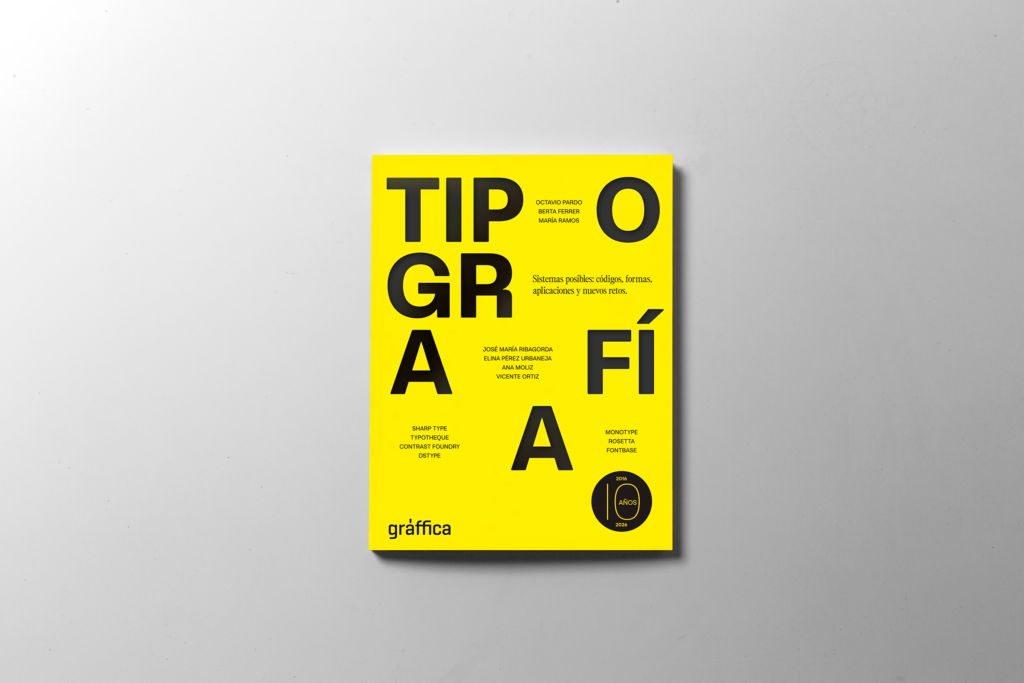
El número incluye entrevistas en profundidad con estudios y actores clave como Sharp Type, Typotheque, Contrast Foundry, DSType, Monotype y Rosetta. Un recorrido que permite entender cómo se está construyendo hoy la tipografía a escala global: desde grandes sistemas tipográficos para plataformas como YouTube hasta desarrollos multiscript de enorme complejidad como Zed, una tipografía pensada para cientos de idiomas y contextos.
Además, esta edición incorpora el espécimen de Zed, un cuaderno de 80 páginas desarrollado por Typotheque que permite explorar en detalle uno de los proyectos tipográficos más ambiciosos de los últimos años. Una pieza que convierte la revista en un objeto editorial aún más completo.
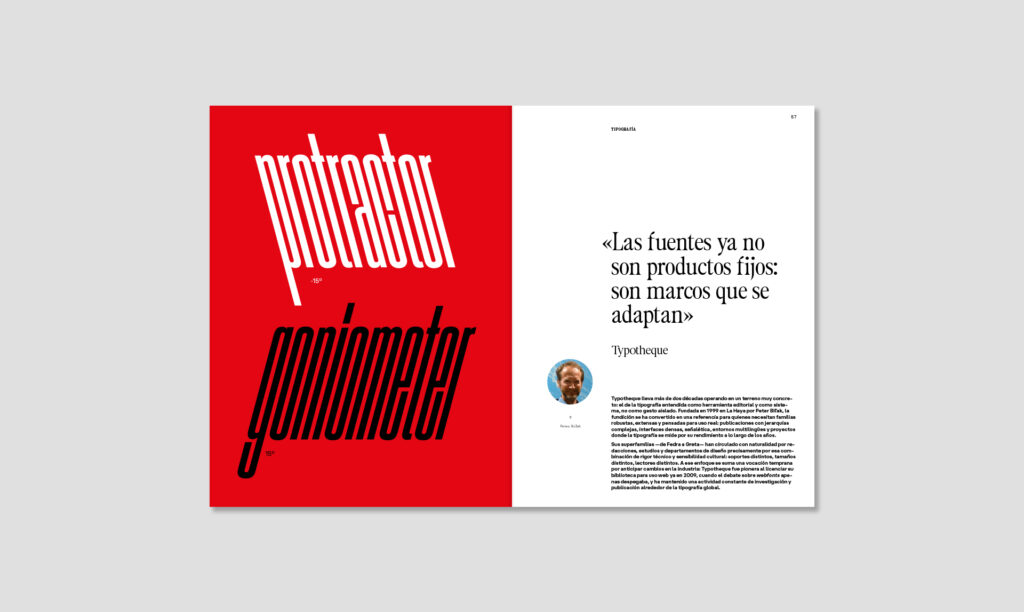
Gràffica Nº41 no es solo una recopilación de referentes, sino también una reflexión sobre el momento actual de la tipografía. A lo largo de sus páginas, el número aborda cuestiones clave como el complejo sistema de licencias tipográficas, el vínculo histórico entre tipografía y tecnología o el cambio de paradigma hacia sistemas paramétricos y nuevas formas de diseño.
El contenido cuenta con firmas como María Ramos, Berta Ferrer, José María Ribagorda, Octavio Pardo o Ana Moliz y Vicente Ortíz, que aportan distintas miradas sobre la disciplina: desde el análisis crítico hasta la exploración de tendencias contemporáneas y movimientos culturales vinculados a la tipografía.
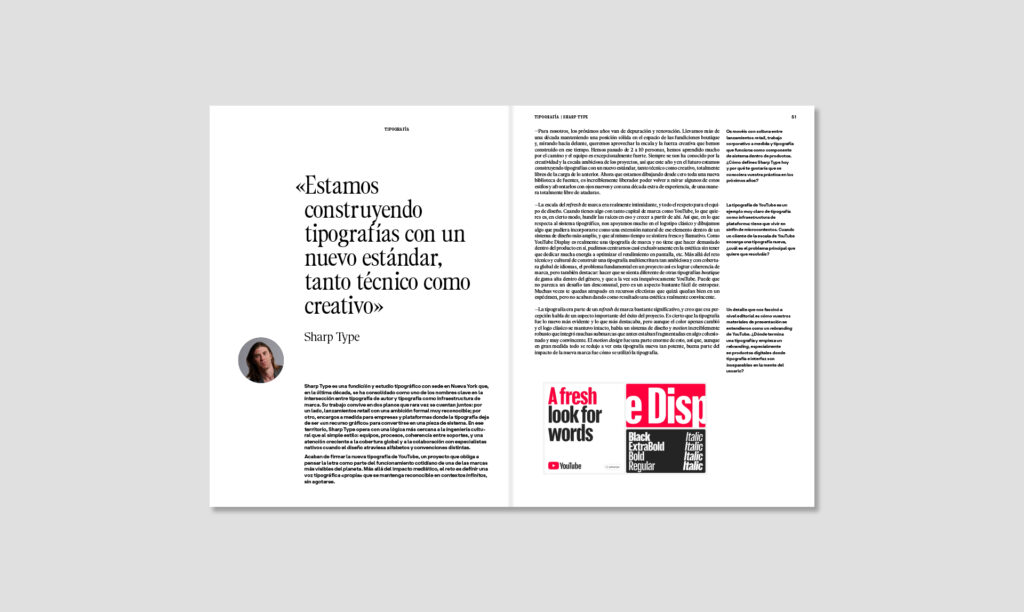
La revista amplía además su mirada con un reportaje sobre el panorama tipográfico en Latinoamérica, firmado por Elina Pérez Urbaneja desde Venezuela, que ofrece una visión directa de un ecosistema en crecimiento. El número se completa con una reflexión sobre la gestión tipográfica junto a FontBase, de la mano de su fundador Dominik Levitsky, que escribe desde Ucrania.
Esta edición tiene además un valor especial: coincide con el décimo aniversario de la revista en papel, consolidando una década de análisis y divulgación en torno al diseño y la cultura visual.
Una publicación pensada para entender la tipografía de hoy… y anticipar la de mañana.